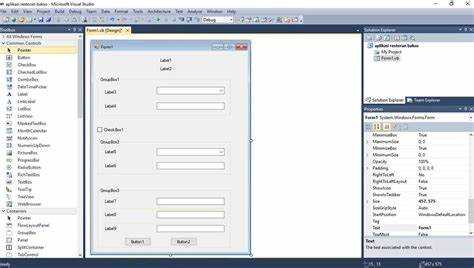
Редактор кода по умолчанию использует моноширинный шрифт Consolas. Этот шрифт поставляется с Windows и оптимизирован для программирования: у него чёткие засечки, стабильная ширина символов и хорошо различимые «0» и «O». Элементы интерфейса Visual Studio (меню, панели, диалоги) обычно отображаются шрифтом Segoe UI, который отвечает за читабельность UI при стандартных масштабах Windows.
Рекомендации по выбору шрифта: Consolas – компактный и нейтральный, работает в любых проектах; Cascadia Code – от Microsoft, поддерживает лигатуры и оптимизирован для терминалов; Fira Code – популярна благодаря лигатурам и хорошему соотношению высоты символа; JetBrains Mono – увеличенный x-height и отличная читаемость при небольших размерах. Для слабой визуальной чёткости выбирайте шрифты с большей высотой символов (x-height) и явно выраженными нулями и запятыми.
Настройки размера и интерлиньяжа: при 100% масштабировании на экране с обычным DPI оптимальны размеры 11–13 pt; при масштабировании 125% и выше – 14–18 pt. Если текст кажется «слипшимся», увеличьте значение Line spacing в настройках редактора или примените системный ClearType (Windows → ClearType), это улучшит сглаживание и разборчивость кода.
Практический стек шрифтов для совместимости и резервного отображения: Consolas, ‘Cascadia Code’, ‘Fira Code’, ‘JetBrains Mono’, monospace. Если вы используете лигатуры – выберите шрифт с лигатурами и убедитесь, что ваша версия Visual Studio их поддерживает (Visual Studio 2019/2022 и новее корректно отображают большинство кодовых лигатур).
Шрифт по умолчанию в Visual Studio: имя и версия
В Visual Studio для редактора кода по умолчанию используется шрифт Consolas. Этот моноширинный шрифт был представлен Microsoft в составе Windows Vista и пакета Microsoft Office 2007, а также входит в стандартный набор Windows 10 и Windows 11.
Consolas разработан Lucas de Groot в 2004 году и с тех пор получил несколько обновлений. В Windows 10 и более поздних версиях используется Consolas версии 5.32. Шрифт оптимизирован для ClearType и поддерживает широкий диапазон символов Unicode, включая математические и технические знаки.
Выбор Consolas объясняется его высокой читаемостью при программировании: символы «0» и «O», «1» и «l» заметно различаются, а межбуквенный интервал сбалансирован для многострочных структур кода. Этот шрифт остаётся стандартным для Visual Studio без необходимости ручной настройки.
Советы и конкретные рекомендации:
Для моноширинного текста используйте: Consolas, Cascadia Code, Fira Code, JetBrains Mono. Эти шрифты читаются лучше в коде и поддерживают специальные символы.
Размер шрифта: обычно 11–13 pt для экранов 96 DPI; для HiDPI (масштаб Windows ≥125%) увеличьте до 14–18 pt. Подберите размер по видимости и объёму кода на экране.
Если хотите включить лигатуры (например для Fira Code или Cascadia Code), выберите шрифт с лигатурами – Visual Studio корректно отображает объединённые символы при поддержке шрифта.
Если настройки не видны или шрифт выглядит размытым, проверьте системный масштаб в Параметры → Система → Дисплей и перезапустите Visual Studio после изменения масштаба.
Для быстрой временной регулировки размера в редакторе используйте Ctrl + колесо мыши (зум редактора); это не меняет глобальные настройки в Options.
Чтобы вернуть стандартные настройки шрифта, откройте Fonts and Colors и нажмите кнопку Use Defaults или восстановите настройки через Import/Export Settings (Tools → Import and Export Settings).
Практические примеры:
Работа с большим проектом на 24″ мониторе: Cascadia Code, 12–14 pt – баланс между читаемостью и количеством кода на экране.
Ноутбук 13″ с высоким DPI: JetBrains Mono, 14–16 pt – четкие символы и комфортная интерлиния.
Если часто используете символы Unicode (→, λ, ●): выбирайте шрифт с широкой поддержкой символов (Consolas или Fira Code).
Проверка и тестирование:
После изменения откройте несколько файлов с разными языками (C#, JavaScript, HTML) и убедитесь, что отступы и выравнивание не нарушены.
Если используется тема с высоким контрастом, проверьте сочетание шрифта и цвета курсора/подсветки – некоторые шрифты хуже выделяются в специфических темах.
Какой шрифт используется по умолчанию в Visual Studio для кода?
В Visual Studio для отображения кода по умолчанию применяется шрифт Consolas. Это моноширинный шрифт, созданный специально для программирования, с ровной шириной всех символов, что облегчает чтение и выравнивание текста. В разных версиях Visual Studio может использоваться небольшая вариация настроек размера и стиля, но основной шрифт остаётся Consolas. Пользователь может изменять его на другие моноширинные шрифты, такие как Courier New или Cascadia Code, через настройки редактора.